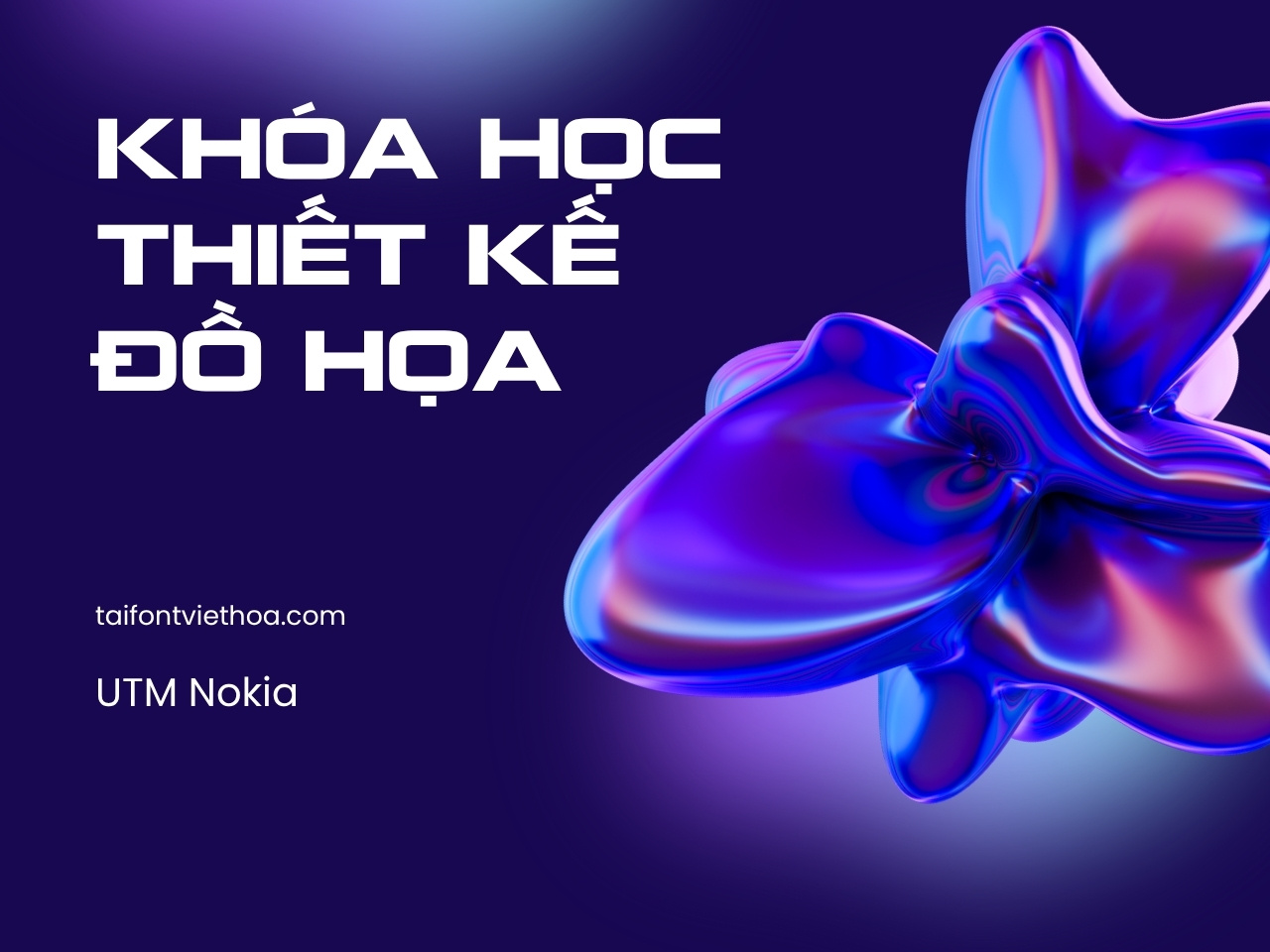
Font việt hóa UTM Nokia đầy đủ
Giới thiệu về font UTM Nokia Trọn Bộ
UTM Nokia Trọn Bộ là phiên bản Việt hóa của bộ font Nokia – một bộ sưu tập font đa dạng, bao gồm nhiều kiểu chữ sans-serif hiện đại và tinh tế, được thiết kế để phục vụ các nhu cầu thiết kế đa dạng từ nhận diện thương hiệu đến giao diện người dùng. Bộ font này nổi bật với các nét chữ thanh mảnh, cân đối và dễ đọc, phù hợp cho nhiều ứng dụng kỹ thuật số và in ấn. Phiên bản Việt hóa đã được hoàn thiện để hỗ trợ đầy đủ tiếng Việt cùng hơn 200 ngôn ngữ khác, mở rộng khả năng sử dụng trong nhiều dự án sáng tạo và chuyên nghiệp.
Font UTM Nokia Trọn Bộ được taifontviethoa.com sưu tầm và lựa chọn kỹ lưỡng nhằm phục vụ cộng đồng thiết kế Việt Nam. Phiên bản Việt hóa giữ nguyên nét hiện đại và tinh tế của bộ font gốc, đồng thời tối ưu khả năng hiển thị tiếng Việt, rất phù hợp cho các dự án branding, quảng cáo và truyền thông đa phương tiện.
Đặc điểm thiết kế và ứng dụng của UTM Nokia Trọn Bộ
UTM Nokia Trọn Bộ bao gồm nhiều biến thể trọng lượng và phong cách, giúp các nhà thiết kế linh hoạt lựa chọn và kết hợp trong các bối cảnh thiết kế khác nhau. Bộ font có cấu trúc sans-serif không chân, với các nét chữ rõ ràng, đồng đều và thiết kế tối giản, mang lại cảm giác hiện đại, chuyên nghiệp và dễ đọc trên nhiều nền tảng.
Font thích hợp sử dụng trong thiết kế website, nhận diện thương hiệu, quảng cáo, bao bì sản phẩm, brochure, poster và các dự án truyền thông đa phương tiện. Các ngành nghề phù hợp gồm: công nghệ, giáo dục, quảng cáo, startup và thương mại điện tử.